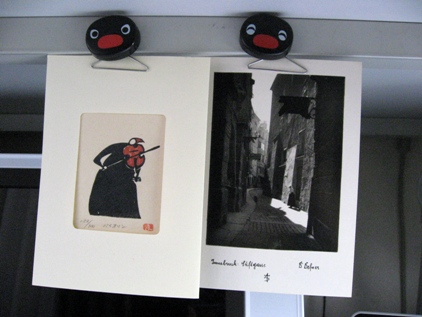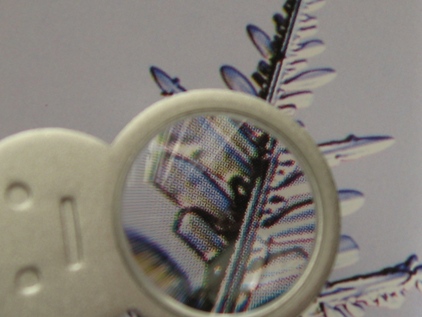
神田探検
今川橋交差点の角
ありますね。
「高野理化硝子」
何か実験の香りが…。
とっても専門的なお店ですけど、
意外や意外
カリだの製本だのに
便利なものたちが
並んでいたりします。
これなんか、セットで250円!
ちょっと
魅力的なピンセット!
竹でできてます。
理科の実験だと何を
つまむの?
金箔とかつまむのはどう?
実験では何に
穴を開けるの?
木みたいに固いものでは
針が折れちゃうけど、
紙なら
穴が開けやすい。
針が細いのが
魅力〜。
他にも糊なんか入れるのに便利な容器とか、あったら可愛いフラスコとか・・・。
またも足を踏み入れると危険な場所を開拓してしまいました。
テュリャテュリャリャ〜。s
玉川高島屋の南館の地価には、楽しいものが
たくさんあります〜。
croissant・クロワッサンというお店は、キッチン周辺の
かわいいものたちが勢ぞろいしていて、うっかりすると
すご〜く長居してしまう・・・ここも近寄ってはいけない危険な
場所かも…フフフ。
さて、先日・・・長居の原因は、キッチンクロス・・・。
日本人なら布巾とおっしゃい!こじゃれた布巾でございます。
どうしたことか7枚〜一週間分なんです!
しかも色違いでございます。
曜日の文字も素敵です。
色については、英語からは
想像つきませんが、
月、火、水・・・と唱えていくと、
何となく火→赤色、水→水色
なのかなぁ〜?
でも日曜と月曜はちと繋がらない
けど・・・。
そういえば、糸を買っても糸巻きしなくて、月曜日に炊いたお風呂に火曜日に入る
ことを自慢するあの女子・・・だれ?
さがります!さがります!
ピンで留めたくないものってありますね…。
跡が残るのを避けたい写真とか…。
こんな便利で可愛いものがあったんです!
PhotoHanger !
ハンガーは洋服をかけるだけじゃないんですね。
ちっこいくせによく挟みます。
挟む方には傷がつきません!
だからお気に入りのポストカードも
ぶ〜らぶら…旅の思い出とともに
ぶら下がり〜。
キッチンであれば、小さいレシピや雑誌から切り抜いたレシピを
ちょいと掛けて…便利かもしれません。
まぁ、まぁ…自分で作ったものをぶ〜らぶら…。
何となく見ていてどんな風に使おうかなぁ〜なんて
ことにも便利です。
こちらも以前ご紹介したアッシュコンセプトのものです。
お部屋に違和感も無くおしゃれです!
雪眼鏡とともに・・・。
「天空から舞い降りた雪の便りを雪眼鏡でご覧ください。」
こんなロマンチックな語りかけをされている馬場威彰氏が
チラチラ舞うダイヤモンドダストにもうっとりしますが、
地上に積もる雪もこれで覗けば、きっと素敵な物語を見ることが
できるでしょう・・・。
あれ?
プリントを覗くとやはり・・・ドットで構成されているのが
見えます〜。
ちょっと目的が違いますが、この世界も面白いものです。
ふ〜ん、ベランダの葉っぱは
フツーでした・・・。
でも緑のお肌はツルツルです!
お日様にあたって栄養満天?
本体を取り出してみると、パッケージの型がかわいい!
すごく小さいんです!携帯にもつけられるくらいの大きさです。
だからスキー場に持っていけます〜!
はい、mojiさんは、雲に乗りビューン、St.Antonで
スキーよりも雪物語にはまる・・・そんな予感がしています。
白い世界へ・・・
みなみな様はいかがなさいましたか?
2日かから走りましたか?
掴みましたか?
覗いてみたりしましたか?
若いお嬢様が白いコートを着ていると
「すてき!」って思うのですが、
年上女子にはちときついです(涙)・・・。
でも冬に白いものはこのうえなく素敵で
ありますね・・・。
スキー場では、白い帽子をかぶっている私でございます。ましろな世界でましろしろ・・・も良いの
ですよ〜!?
2日のバーゲンには完全に出遅れましたが、4日はちょっとだけ・・・前から欲しかったましろな手袋!
あったんです!なので早速ゲットです。
この白い革手袋の白いステッチ!手首も白いニット!
ぁあ〜年上女子には有難いましろな小物です〜。
・・・さて、もうすぐましろな世界へ足を運ぶ予定です・・・。
青い空を除けばどこもかしこも白い、白い・・・。雪山さん、待ってて
くださいね!
「Ho ! Ho ! Ho !・・・待ってるよ!」
「も、もしやあなたは・・・?」
「クリスマスは働いたでのぅ〜!
休暇もらってスキーじゃよ。ルドルフも
もうすぐやってくるんじゃよ!」
1.Paper & Ink の筆入れです。
おまけに以前ブログでご紹介したこともあるドクター・マーチンの
パレット(未使用)をおつけします。
メルマガにはJohn Neal の筆入れと書いてありますが間違いでした。すみません・・・。筆入れを目の前にして他の名前を書く
なんて〜ぁあ・・・脳が・・・
どちらもすごく重宝しますよ!
特に筆入れは道具運びに最適です
2.Sheila Waters 作品 カラー(プリント)、マット付き
カリを愛する世界中の人から尊敬を集めるシーラです。
その正確で美しい文字と装飾は、皆の憧れでもあります。
作品をまだ作ったことがない人もどうやってレイアウト
するのか・・・とか、どんな配色をするのか・・・などなど
著名なカリ人の作品は、必ずあなたを助けてくれます。
お嬢さん!本当です!
シーラは、有名カリ人ジュリアンのお母様〜
3.Sheila Waters 作品 ゴシサイズドイタリック(プリント)
シーラのゴシサイズドイタリックは、優雅で品があります。
国内では比較的人気のある書体でしょうか・・・。
日頃からお側に置いて、眺めましょう〜。
いつかこんな美しい作品が書けるかも・・・しれません
見れば見るほど・・・美しい〜。
4.Gottfried Pott 作品 フォルダ入り(プリント6枚)
こちらはドイツの巨匠!ゴットフリードの作品です。
ルーリングペンをカリ世界に広めたその貢献度は
計り知れません。
力強い作品を見れば、線そのものの勢い、美しさを
発見できるはずです!
5.David & Nancy Howells 作品
フォルダ入り(コピー10枚)
様々な文字のバリエーションが詰まっています!
自分自身の文字を探しているお嬢さん・・・、必見です。
作品を包んである紙までカッコイイ!さすが〜なカリ人です。
6.Tシャツ Denis Brown デザイン
(男性Mサイズ)
最近日本でWSし続けていたDenisの若かりし頃・・・、
(今も若い?)のも・・・だと思います。
大き過ぎて着られなくても飾っておけるほど完成度高い
美しいカリグラフィーです
7.Skriptorium (ドイツ語版)
中世写字室について、そして
ギルディングなどの技法について
カラー48ページ
面白い縦長の本です。
中世の写本の世界と技術的なことや画材などのお話しが載って
います。
言葉がわからなくても、カラーページばかりなので、写真が
美しく眺めているだけでも飽きません〜!
一応、スイスのサンクト・ガレンで購入したものです。
その空気も伝わるでしょうか〜
以上7点を提供致します。
どうぞ皆様が気に入ってくださいますように〜!
アンティークフェア
さて、イギリスへ行ったら何と言ってもアンティークです。
ここは昨日ご紹介したDurhamの大聖堂の横にある大学の学生たちがディベートに使う講堂です。ここを夏休みの間だけけ使ってアンティークフェアが開かれています。
入場料がかかりましたが、そこでお宝グッズをたくさん発見!興奮状態!
最初入るかどうか迷った時に、ペンナイフはありますか?と聞いたところあるよとのことだったので行ってみると、ペンナイフ=小さな折りたたみ式ナイフでした。そうそう、そうだった。私たちが通常言ってるペンナイフは、クイルカッターと言わないと通じないのでした。そこでそう聞いてみると、はいあるよ、と出してくれたのがこの古いインク壷の前に置いたこれです。ちいさなバターナイフの様ですが、昔はこれで羽ペンを削っていたんですね。
古いインク壷たちも素晴らしいです。いろいろな形があるんですね〜〜。
こちらはふるーいインクです。このぼろぼろなのはウインザー&ニュートン。もう50年近く経っていますがまだ液体が少々残っていました。
そんなものがもうたっくさんあって、キャーキャー見つけるたびに大騒ぎです!
そして極めつけはこれ!
こんなの見たことありませんでした。
これはpounce pot(パウンスポット)と言って、粉を入れて振る道具です。パウンスとはガムサンダラックやパミスなどの粉の総称を言います。紙や羊皮紙にインクで書く時細くてきれいな線を出すために、ガムサンダラック、羊皮紙を書くための準備として表面の油分を取り、また表面に毛羽を立たせるためにはパミスを使います。それらをムラなくかけるための道具があったとは!・・・・・・。ひょ〜!
おみやげいろいろ
しか〜し! ことアルファベットに関しては、やはり本場にはかないまへん。この可愛いこと、そして種類の豊富さ!
これはアメリカからのおみやげです。すごいでしょ〜!もったいなくて、とても使えません。
いろいろなテーマ別の文字になっているんですね。ふむふむ、すごい数のシールです。
さてもうひとつオマケが付いていました。
それは、このno blot pencilです。
水をつけると滲むエンピツ?
鉛筆本体には
Bottle of ink in a pencil.
なんて書いてあります。
水彩色鉛筆の様ですが、ここまで滲まないですよね。
おもしろ〜い。書いてから水を塗ってもいいし、さっと水を引いた上に書いてみても楽しい結果になりました。
しかし、一体何のために・・・??
いやいや、そんな野暮な事を聞くのはやめましょう。楽しい雑貨、文房具であれば良いのです。